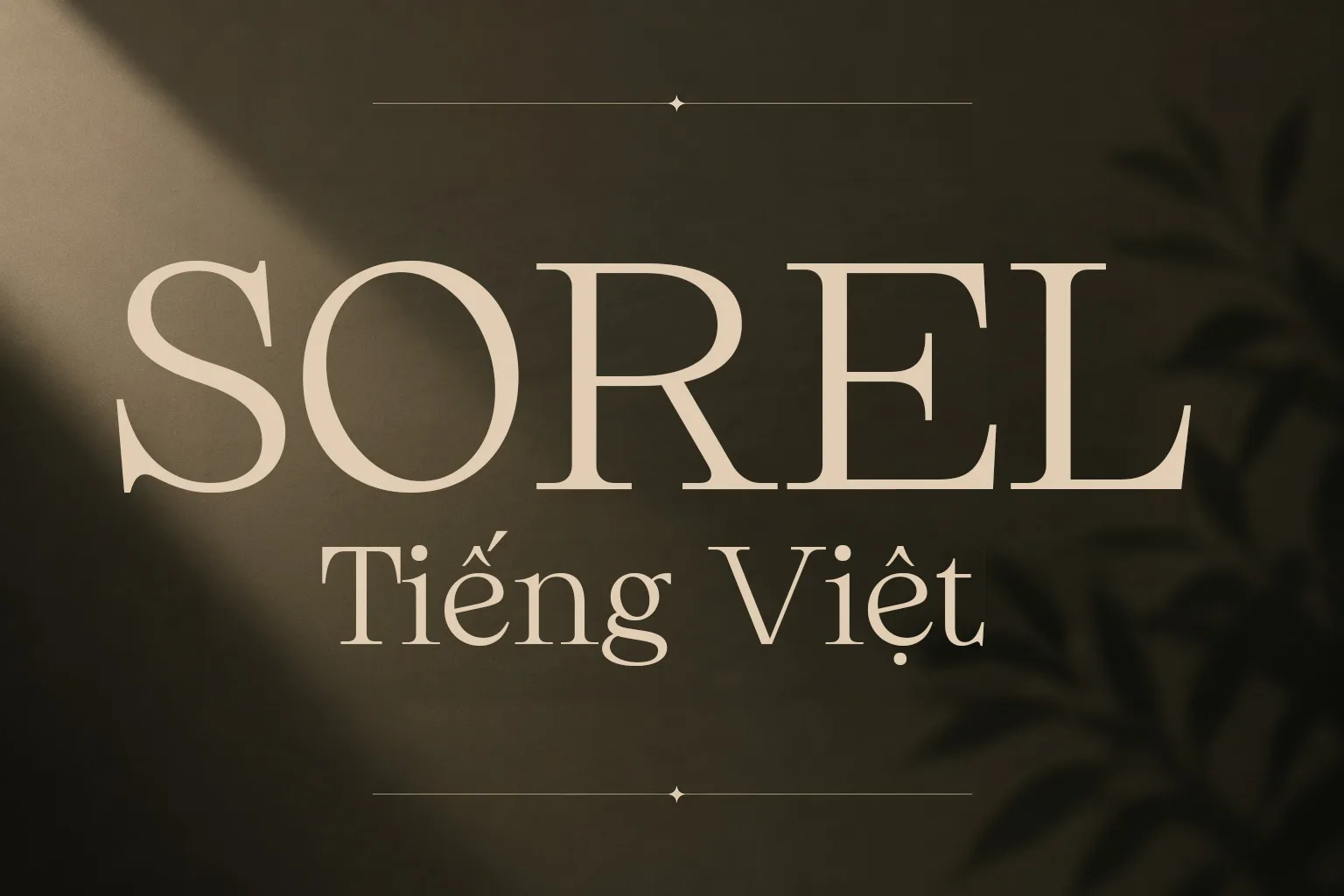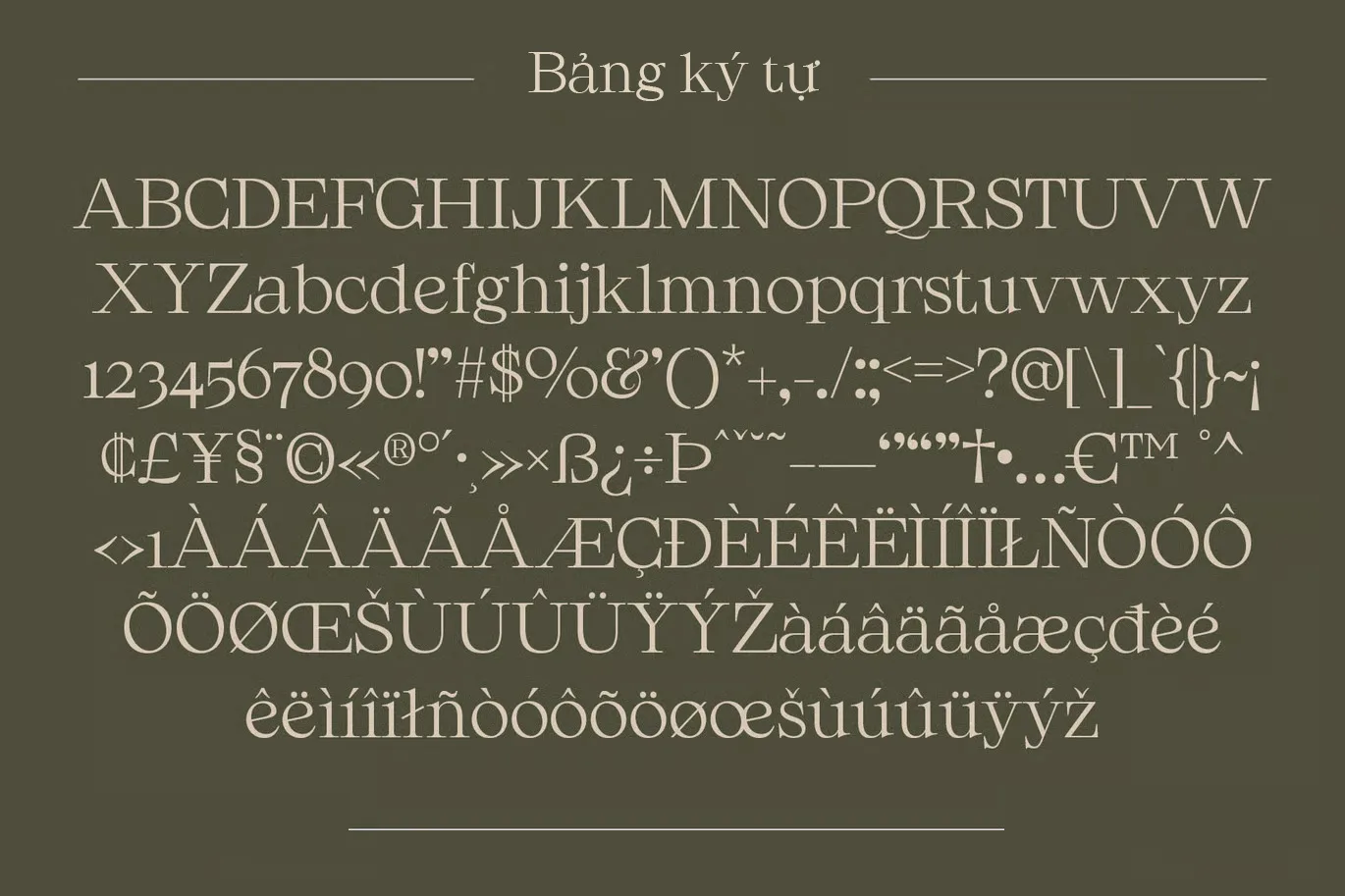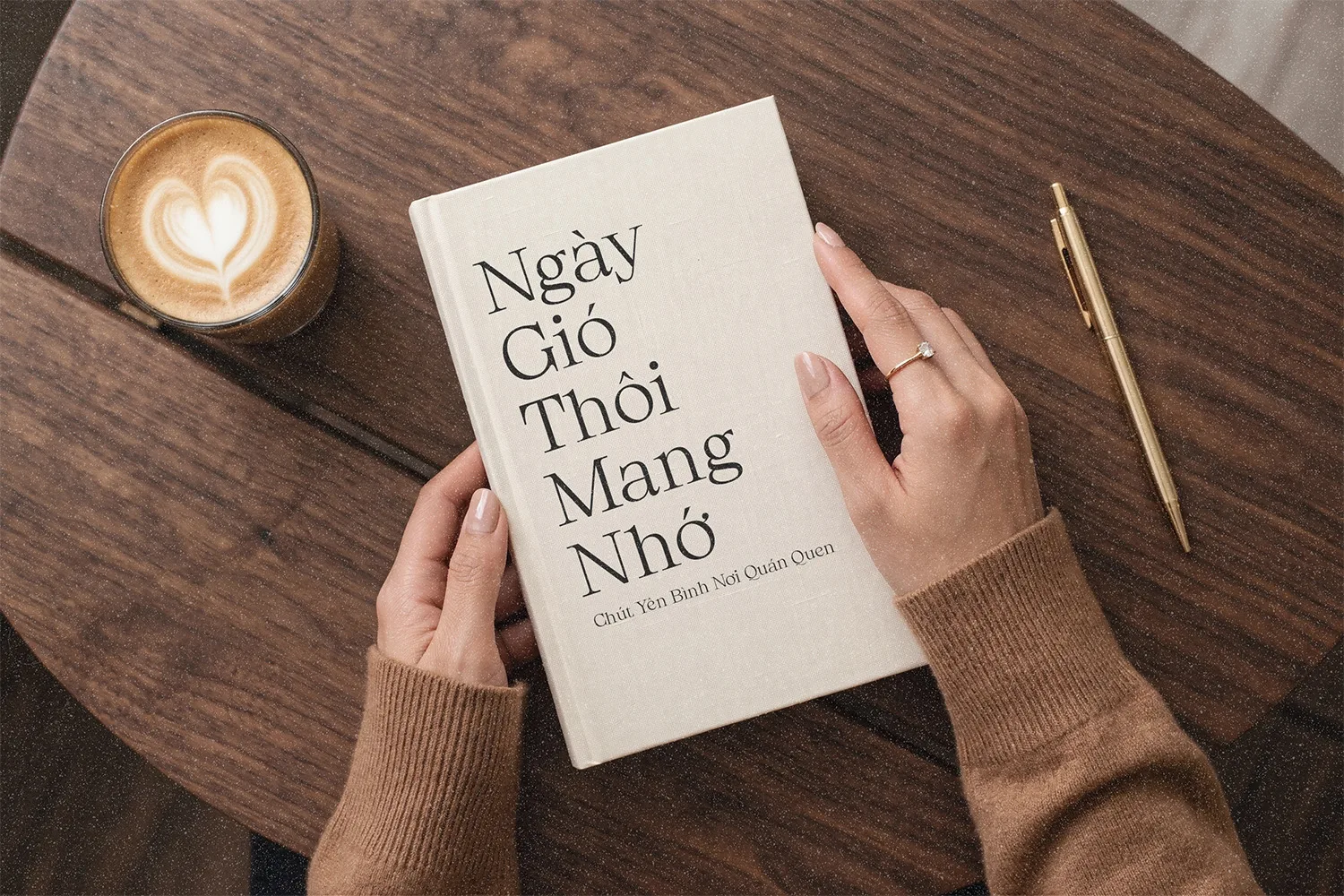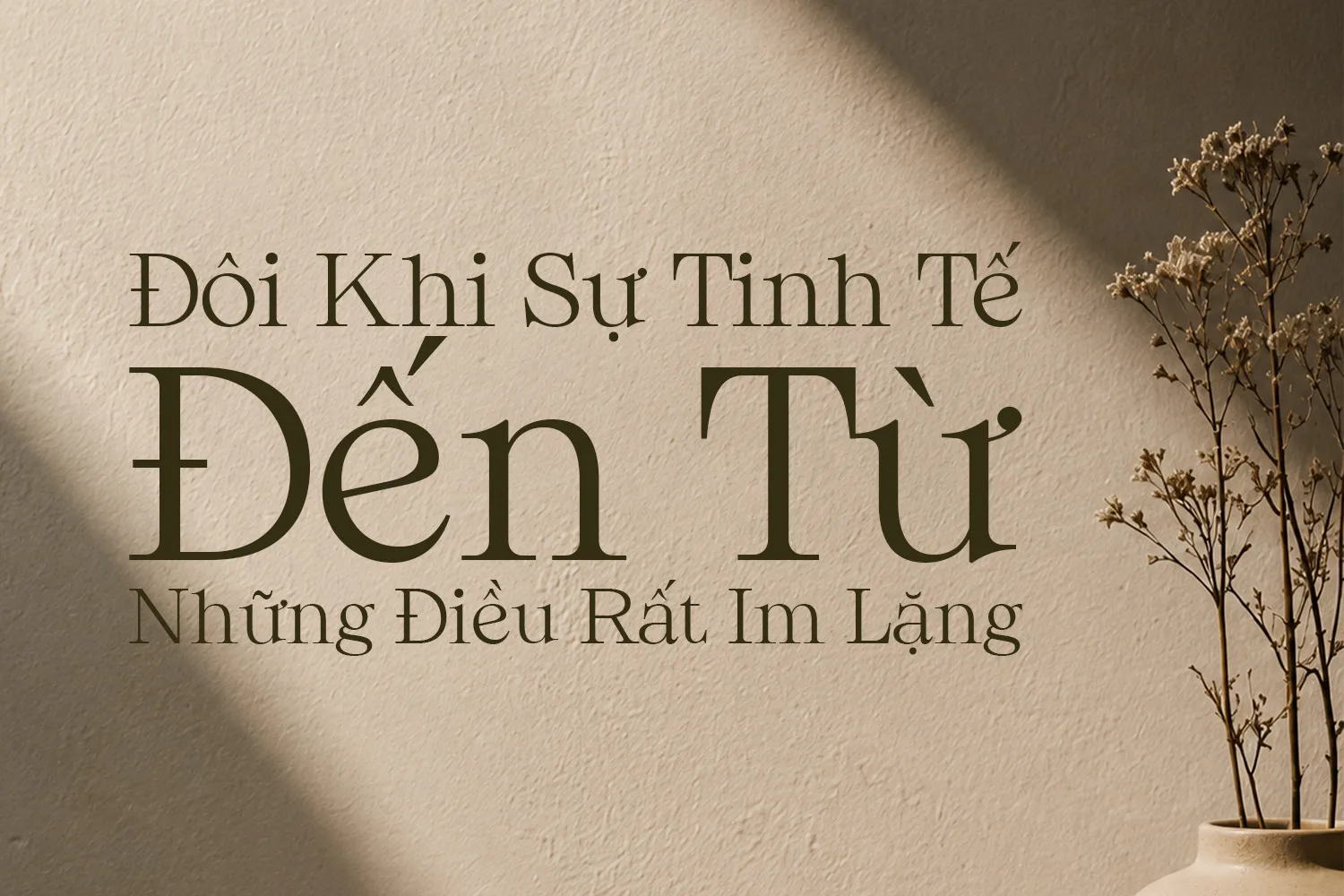
DVN Sorel tiếng Việt – Font chữ Serif cao cấp và hiện đại
DVN Sorel tiếng Việt là kiểu font serif mang vẻ đẹp thanh lịch và thời thượng, lấy cảm hứng từ phong cách editorial cao cấp và tinh thần thời trang hiện đại. Những đường nét mảnh mai kết hợp cùng độ tương phản tinh tế tạo nên cảm giác sang trọng, mềm mại nhưng vẫn đầy cá tính.
Phù hợp cho thiết kế branding, logo, poster, tạp chí, beauty, wedding, fashion và các dự án cần vẻ đẹp tối giản đậm chất luxury. Bộ ký tự tiếng Việt được tối ưu chỉn chu giúp từng con chữ hiển thị hài hòa và cuốn hút trong mọi bố cục thiết kế.